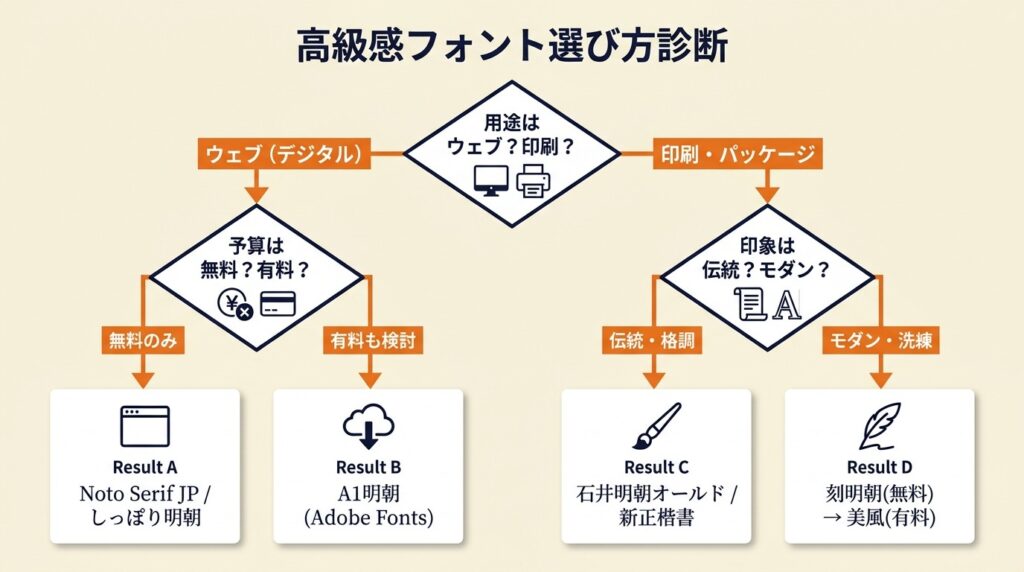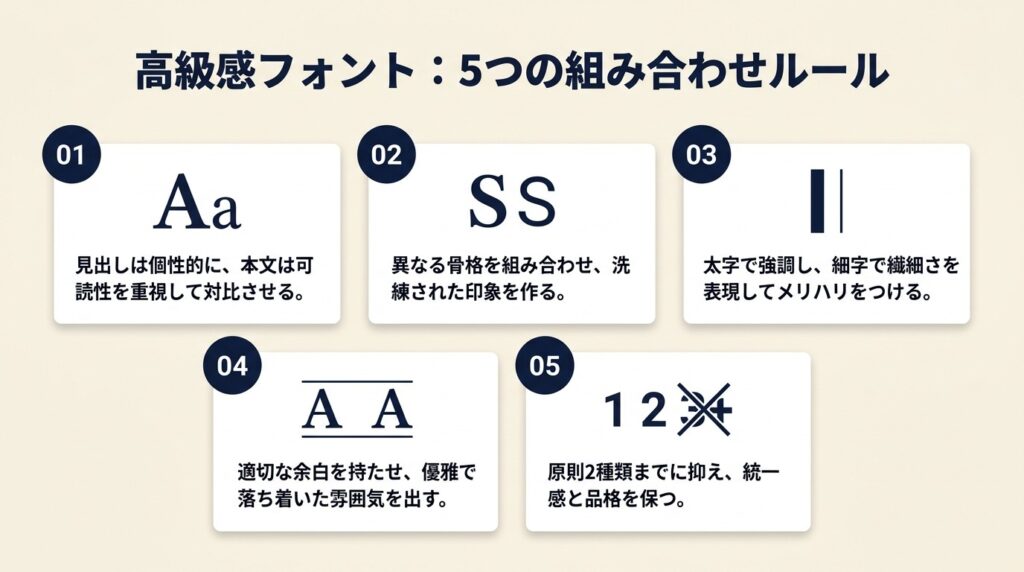
デザインに高級感を出したいなら、明朝体フォントの選択が最短ルートです。無料で使える源ノ明朝から有料のMorisawaシリーズまで、用途別に15本を厳選しました。商用利用の可否と導入方法もあわせて解説します。
高級感を演出するフォントは「明朝体の選択」と「ウエイトの使い分け」の2点で決まります。無料なら源ノ明朝(Google Fonts)、有料ならMorisawa Fontsの石井明朝シリーズが最初の選択肢です。用途に応じてウェブ向け・印刷向け・ロゴ向けを使い分けることで、デザインの完成度が大きく変わります。
高級感フォントは明朝体とゴシック体で選ぶ
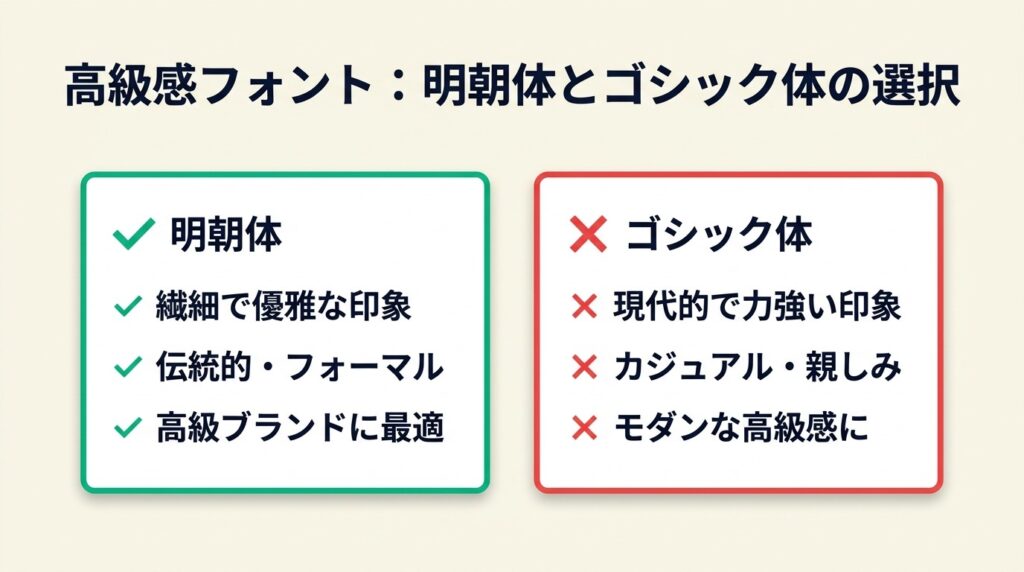
フォント選びで「なんとなく高級感が出ない」と感じる原因の多くは、書体カテゴリの選択ミスにあります。明朝体とゴシック体それぞれの特性を理解することが、高級感演出の出発点です。
明朝体は縦横の線の太さの差が高級感を生む
明朝体の最大の特徴は、縦線が太く横線が細い「線の強弱」にあります。この強弱が視覚的な緊張感と品格を同時に生み出し、読者に「丁寧に作られた印刷物」という印象を与えます。新聞の見出しや高級ブランドのパッケージに明朝体が多用されるのはこの理由からで、単なる慣習ではなく視覚心理に基づいた選択です。「高級感 = 明朝体」という図式は、デザイン初心者にとって最も再現性の高いスタート地点です。
ゴシック体は均一な線幅がモダンな高級感を生む
ゴシック体は縦横の線幅がほぼ均一で、無駄を削ぎ落とした現代的な美しさを持ちます。ラグジュアリーブランドのロゴが示すように、「余白と均一性」によって高級感を演出する手法です。日本語ゴシック体では、ウエイトをExtraLightまで落とすことで同様の効果を得られます。明朝体とゴシック体はどちらが優れているわけではなく、「伝統的・格調高い高級感」か「モダン・ミニマルな高級感」かという方向性の違いです。
高級感を破壊する3種類のフォントの特徴
避けるべきフォントの特徴は「線幅が均一でポップな丸ゴシック」「手書き風の崩れた筆致」「装飾過多なデコレーション系」の3種類です。これらはカジュアルさや親しみやすさを演出する目的では有効ですが、高級感とは相反する視覚的メッセージを送ります。よくある誤解として「游ゴシック Mediumを選べば高級になる」というものがありますが、游ゴシックはあくまで可読性重視の中庸フォントであり、高級感の演出には別途工夫が必要です。フォント選定の段階でこの3種を除外するだけで、デザインの底上げが実現します。
ウエイト選択が高級感の完成度を左右する
同じフォントファミリーでも、ウエイト(太さ)の選択によって印象は大きく変わります。見出しにはHeavy/Boldを使いつつ、本文にはLight/Thinを採用することで、コントラストが生まれ紙面に奥行きが出ます。逆に全要素をRegularで統一すると、フラットで安価な印象になります。ウエイトを2種類以上使い分けることが、フォント選定と同等かそれ以上に重要な技術です。日本語フォント無料おすすめ12選では商用利用可能な無料フォントのウエイト活用事例も紹介しているので、あわせて参考にしてください。
Q: 明朝体とゴシック体はどちらが高級感を出しやすいですか?
A: 目的によって異なります。格調・伝統・和の高級感には明朝体、モダン・ミニマル・洋の高級感にはゴシック体(特に細いウエイト)が適しています。ウェディングや旅館・和食店向けなら明朝体、アパレルや建築デザイン向けならゴシック体から始めると選択しやすいです。
Q: 丸ゴシックで高級感を出すことはできますか?
A: 非常に難しいです。丸ゴシックは線端が丸く処理されており、視覚的に柔らかくカジュアルな印象を与えます。高級感を求める用途では避けてください。どうしてもゴシック系を使う場合は、線端が直角に切られた「角ゴシック」のExtraLightウエイトを選んでください。
無料で使える高級感フォントは5本が定番
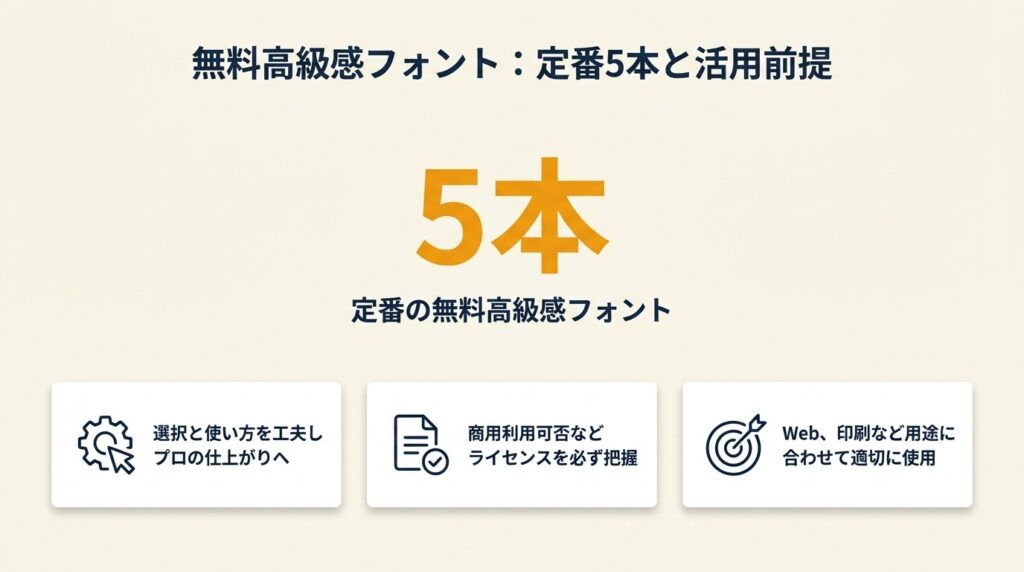
無料フォントでも選択と使い方を工夫すれば、十分にプロフェッショナルな仕上がりが得られます。ライセンスと用途を把握した上で使うことが前提です。
源ノ明朝(Noto Serif JP)はGoogle Fontsで7ウエイト無料
源ノ明朝はAdobeとGoogleが共同開発した高品質明朝体で、ExtraLight/Light/Regular/Medium/SemiBold/Bold/Blackの7ウエイトを無料で利用できます。Google Fontsから「Noto Serif JP」として配信されており、商用利用・ウェブ埋め込みともに無制限で可能です(SIL Open Font License 1.1)。7ウエイトが揃っているため、タイトルから本文・キャプションまで1フォントファミリーで階層設計できる点が他の無料明朝体にない強みです。無料フォントの中で最も汎用性が高く、迷ったらまずNoto Serif JPが定石です。
はれのそら明朝はCanvaで使えるスタイリッシュな和文明朝体
はれのそら明朝は、縦組みにも横組みにも対応した現代的な明朝体で、Canvaに搭載されています。ウエイト数は1種類のみですが、そのRegularウエイトが洗練されており、招待状・メニュー表・プロフィールカードなどのブライダル・ブランディング用途に適しています。Canvaユーザーであれば追加のインストール作業なしに即使用でき、コスト0円で高級感のある和文デザインが完成します。ただし、Canva以外のデザインツールへの移植は利用規約上制限があるため、Canvaでの完結が前提となります。
刻明朝はフォントワークスが無料公開した格調ある明朝体
刻明朝はフォントワークス(Fontworks)が2021年にGitHubで無料公開した明朝体で、SIL OFLライセンスにより商用利用が可能です(Fontworks GitHubページ)。伝統的な刻りを意識した字形が特徴で、出版・パッケージ・和風ブランディングに高い親和性があります。1ウエイトのみですが、字形の品質がフリーフォントの中では高く、商用ロゴへの使用実績も多くあります。無料明朝体の中で「本物感」を求めるなら最初に試す価値があります。
851ゴチカクットはゴシック系でモダンな高級感を出す無料選択肢
851ゴチカクットは線端を直角に処理した角ゴシック体で、1ウエイトながらシャープな視覚印象があります。SIL OFLライセンスで商用利用可能で、ECサイトのバナー・SNS告知・ミニマルデザインの見出しに適しています。明朝体では「古典的すぎる」と感じるモダンなブランドにとって、無料ゴシック系の有力候補です。白背景に851ゴチカクットの大きいサイズのテキストを置くだけで「シンプルだが安っぽくない」という印象を得られます。
しっぽり明朝はウェブ特化の無料明朝体で読みやすさと高級感を両立
しっぽり明朝はGoogle Fontsから配信されており、ウェブでの日本語表示に最適化された明朝体です。ExtraLight/Light/Regular/Medium/Boldの5ウエイトが揃い、スマートフォン・PCどちらの画面でも視認性が高く保たれます(Google Fonts: Shippori Mincho)。Noto Serif JPと比較すると文字のアクがやや強く、和のテイストをより前面に出したい場合の差別化として機能します。ウェブサイトのブログ記事・商品説明文を品格のある印象に変えたいならしっぽり明朝が最適です。無料文字フォントは商用利用可が300種以上の記事では、ライセンスの見分け方も詳しく解説しています。
Q: Canvaの無料プランで高級感フォントは使えますか?
A: はい、はれのそら明朝を含む一部の和文明朝体は無料プランでも利用可能です。ただし、Canva Proに限定されるフォントも多く存在するため、使用前にフォント名の横にある王冠マーク(Pro限定の印)を確認してください。
有料の高級感フォントは品質と自由度で選ぶ
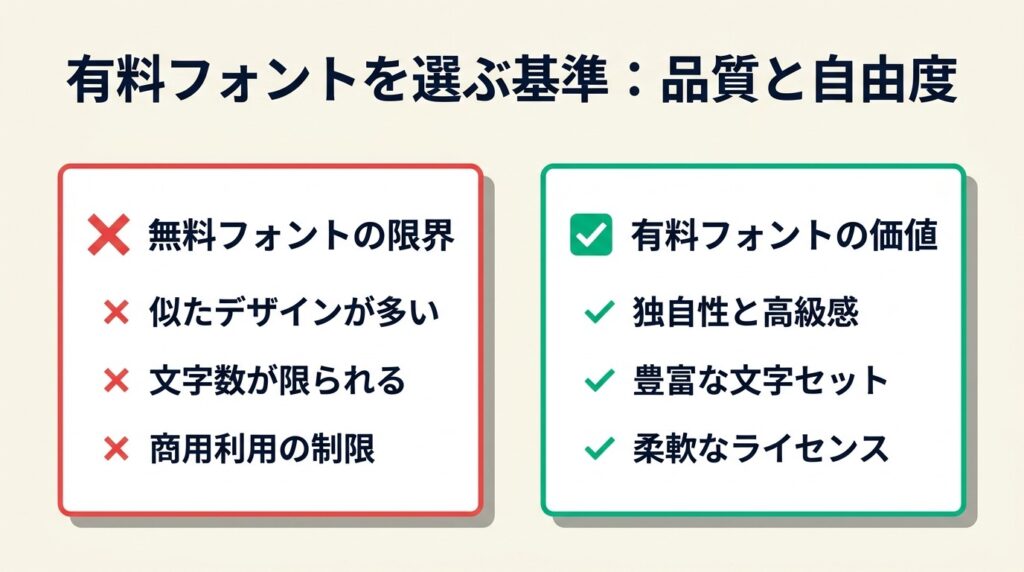
無料フォントで限界を感じ始めたとき、有料フォントへの投資を検討するタイミングです。費用対効果の観点から、有料を選ぶべき条件と主要フォントを整理します。
石井明朝シリーズはMorisawa Fontsの高級感フォントの中核
石井明朝はMorisawa(モリサワ)が提供する明朝体の代名詞的存在で、複数のウエイトが揃います。「オールドスタイルかな」のバリエーションでは、昭和初期の活版印刷を思わせる仮名字形が採用されており、老舗ブランド・出版・高級旅館のブランディングに一貫した使用実績があります(Morisawa Fonts 公式サイト)。有料フォントの中でも石井明朝は「歴史ある格調」を最も直接的に表現できるフォントです。導入にはMorisawa Fonts契約が必要ですが、多数のフォントが使い放題になるため、複数フォントを使う制作者には費用対効果が高い選択です。
Q: フォントのウエイト数が少ない(1〜2種類)のは使いにくいですか?
A: 1〜2ウエイトのフォントは使用用途を絞る必要がありますが、使いにくいわけではありません。タイトルや見出し専用として割り切って使用し、本文には別の多ウエイトフォントを組み合わせることで十分なデザイン階層を作れます。石井明朝を見出し専用に使い、本文にNoto Serif JPを当てるという組み合わせが実用的です。